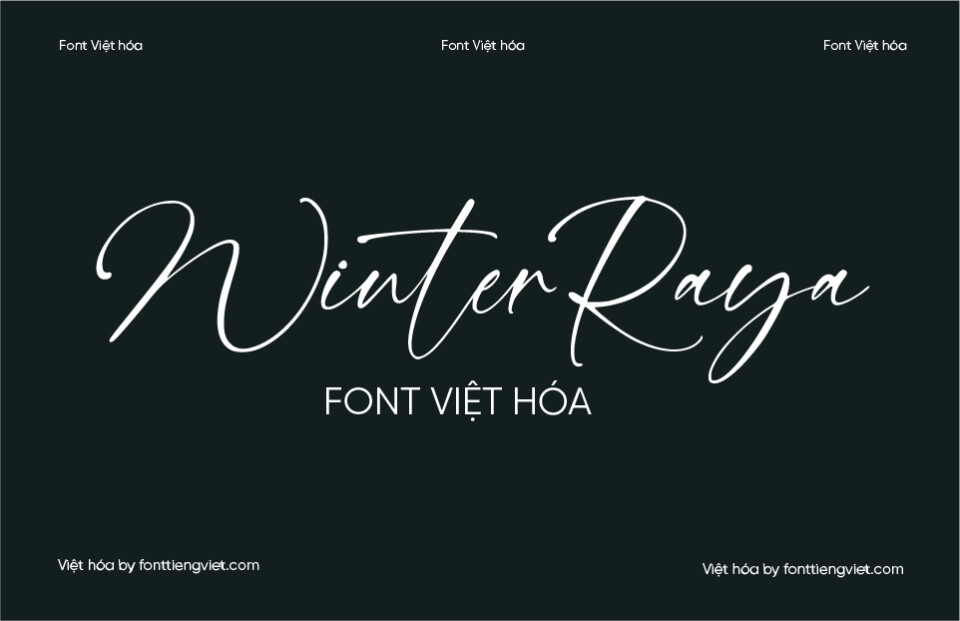
Khám Phá Sức Hút Của Font Việt hóa 1FTV VIP WinterRaya: Tuyệt Phẩm Thiết Kế Cho Học Sinh và Sinh Viên
Trong thế giới thiết kế đồ họa và nội dung số, việc lựa chọn một bộ Font Chữ phù hợp có thể tạo nên sự khác biệt lớn, đặc biệt đối với học sinh, sinh viên đang thực hiện các dự án học tập hoặc bài thuyết trình. Một cái tên đang gây sốt trong cộng đồng sáng tạo gần đây chính là Font Việt hóa 1FTV VIP WinterRaya. Đây không chỉ là một bộ font đơn thuần mà còn là một công cụ mạnh mẽ giúp nâng cao tính thẩm mỹ và chuyên nghiệp cho mọi ấn phẩm. Với phong cách độc đáo, sự mượt mà trong nét chữ, WinterRaya đã nhanh chóng trở thành lựa chọn hàng đầu cho các nhà thiết kế trẻ, những người đang chuẩn bị cho các kỳ thi quan trọng hoặc cần tạo ra một portfolio ấn tượng.
Sự Việt hóa hoàn chỉnh của bộ font này đảm bảo rằng mọi dấu câu và ký tự đặc biệt trong tiếng Việt đều được hiển thị một cách chính xác, loại bỏ hoàn toàn nỗi lo về lỗi font thường gặp. Hãy cùng chúng tôi đi sâu vào khám phá tại sao Font Việt hóa 1FTV VIP WinterRaya lại được săn đón đến vậy và làm thế nào nó có thể hỗ trợ tối đa cho quá trình học tập và sáng tạo của bạn.
Đặc Điểm Nổi Bật Của Font Việt hóa 1FTV VIP WinterRaya và Lợi Ích Cho Học Đường
Điều làm nên sự đặc biệt của Font Việt hóa 1FTV VIP WinterRaya chính là sự kết hợp hài hòa giữa tính nghệ thuật và khả năng đọc. Bộ font này được thiết kế với cảm hứng từ mùa đông (Winter) và sự rực rỡ (Raya), mang lại cảm giác vừa ấm áp vừa tươi mới. Đối với học sinh cấp ba, sinh viên đại học, những người thường xuyên phải làm việc với các báo cáo học thuật và bài thuyết trình, một bộ font đẹp, rõ ràng là cực kỳ quan trọng.
Sự mượt mà và tính nhất quán của bộ font này giúp các tài liệu học tập trở nên dễ đọc hơn, giảm thiểu sự mệt mỏi cho người đọc, điều này rất quan trọng khi ôn thi tốt nghiệp trung học phổ thông. Việc sử dụng các kiểu chữ độc đáo như thế này trong các dự án sáng tạo không chỉ thể hiện gu thẩm mỹ cá nhân mà còn giúp bài làm của bạn nổi bật giữa đám đông.
Tối Ưu Hóa Bài Thi Tốt Nghiệp và Dự Án Trường Học
Trong bối cảnh cạnh tranh học thuật ngày càng cao, việc trình bày khoa học và ấn tượng là một lợi thế lớn. Font 1FTV VIP WinterRaya cung cấp nhiều biến thể kiểu chữ (style variants) cho phép bạn linh hoạt áp dụng vào các loại hình nội dung khác nhau. Chẳng hạn, bạn có thể sử dụng phiên bản Regular cho nội dung chính của luận văn và phiên bản Bold hoặc Italic cho các tiêu đề phụ hoặc điểm nhấn quan trọng.
Ứng Dụng Trong Học Tập và Thiết Kế Đồ Họa
Không chỉ dừng lại ở các tài liệu văn bản, Font Việt hóa 1FTV VIP WinterRaya còn là trợ thủ đắc lực trong lĩnh vực thiết kế đồ họa học đường. Bạn có thể sử dụng font này để thiết kế poster quảng bá sự kiện của trường, tạo infographic tóm tắt kiến thức, hoặc thậm chí là thiết kế bìa sách, bìa luận án tốt nghiệp. Sự linh hoạt của nó đáp ứng được nhu cầu của cả những người mới bắt đầu học thiết kế lẫn những sinh viên chuyên ngành đồ họa.
Nhiều chuyên gia SEO content và nhà thiết kế khuyên dùng các font chữ có tính thẩm mỹ cao để tăng cường sự thu hút của nội dung số, và WinterRaya chính là một lựa chọn không thể bỏ qua. Nó giúp các dự án của bạn trở nên sinh động hơn, truyền tải thông điệp một cách rõ ràng và chuyên nghiệp hơn, đặc biệt quan trọng trong các bài thuyết trình cuối kỳ.
Sự đầu tư vào bộ Font Việt hóa chất lượng như thế này là sự đầu tư vào hình ảnh cá nhân và chất lượng công việc. Hãy tưởng tượng một bài tiểu luận được trình bày bằng một kiểu chữ nhàm chán so với một bài tiểu luận sử dụng 1FTV VIP WinterRaya: sự khác biệt về mức độ thu hút và ấn tượng đối với giáo viên chấm điểm là rất lớn. Đây là một chi tiết nhỏ nhưng lại đóng vai trò quyết định trong việc tối ưu hóa điểm số và sự công nhận trong môi trường học thuật.
Để tận dụng tối đa, hãy đảm bảo bạn sử dụng font này một cách có chủ đích. Kết hợp nó với các màu sắc phù hợp trong bản trình bày để tạo ra sự tương phản tối ưu, giúp bài giảng hoặc báo cáo của bạn đạt hiệu quả cao nhất. Việc này đặc biệt hữu ích cho các buổi bảo vệ đồ án tốt nghiệp, nơi mà sự chuyên nghiệp trong từng chi tiết nhỏ nhất đều được đánh giá cao.
Tóm lại, Font Việt hóa 1FTV VIP WinterRaya là một tài nguyên quý giá cho bất kỳ ai hoạt động trong lĩnh vực giáo dục và sáng tạo, từ học sinh cấp ba đến các sinh viên chuẩn bị tốt nghiệp. Nó mang lại vẻ ngoài chuyên nghiệp, tinh tế cho mọi dự án, từ bài tập về nhà đến các ấn phẩm truyền thông của trường. Đừng ngần ngại khám phá và tải về bộ Font Chữ đặc biệt này để nâng tầm chất lượng các sản phẩm thiết kế của bạn ngay hôm nay. Sự khác biệt về mặt thị giác mà Font Việt hóa 1FTV VIP WinterRaya mang lại chắc chắn sẽ giúp bạn gặt hái được nhiều thành công hơn trong học tập và công việc.